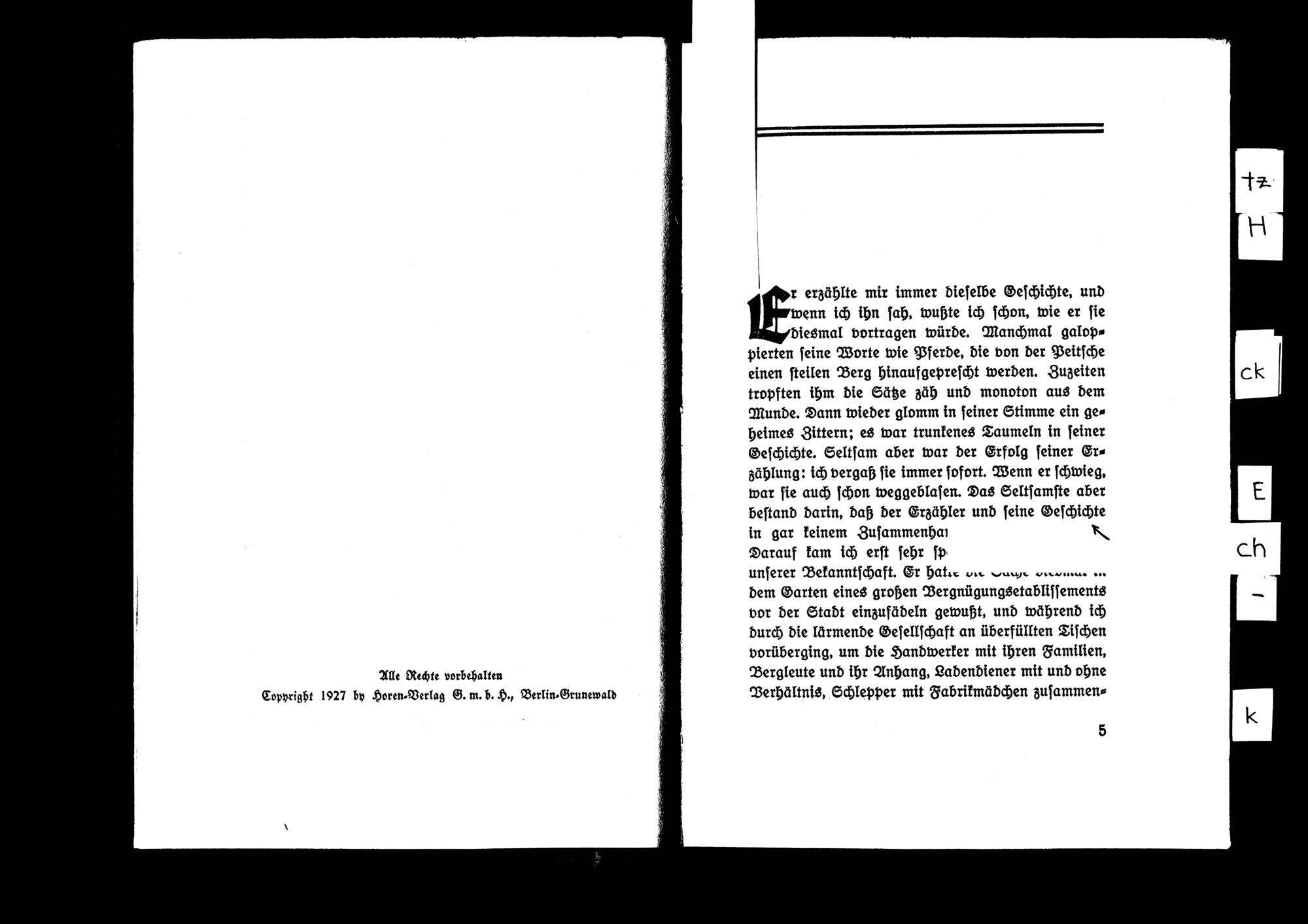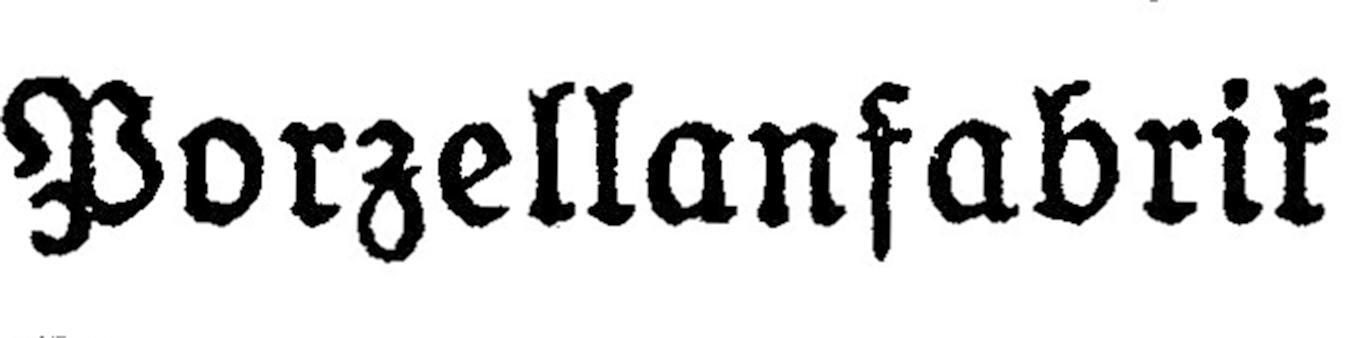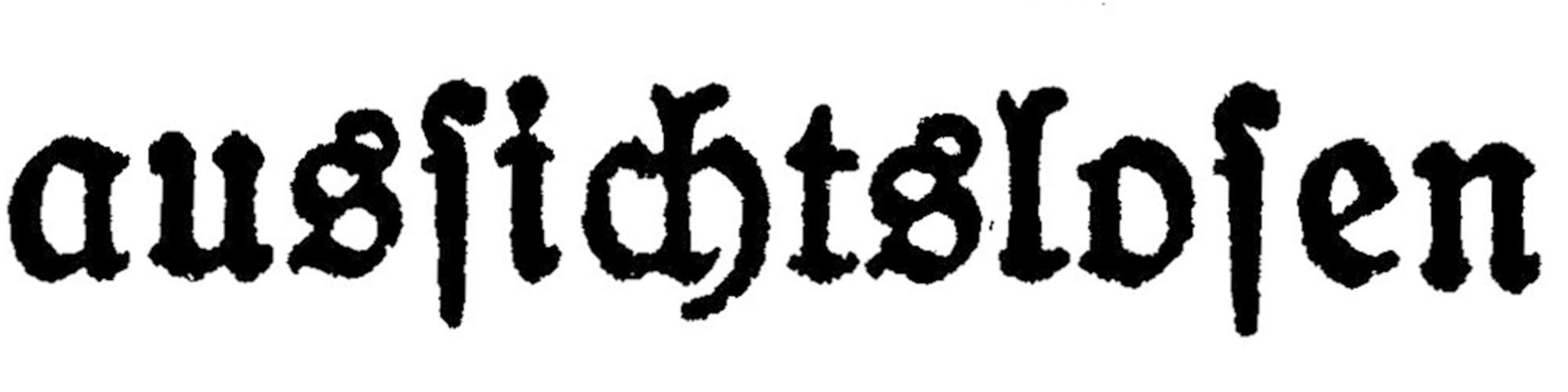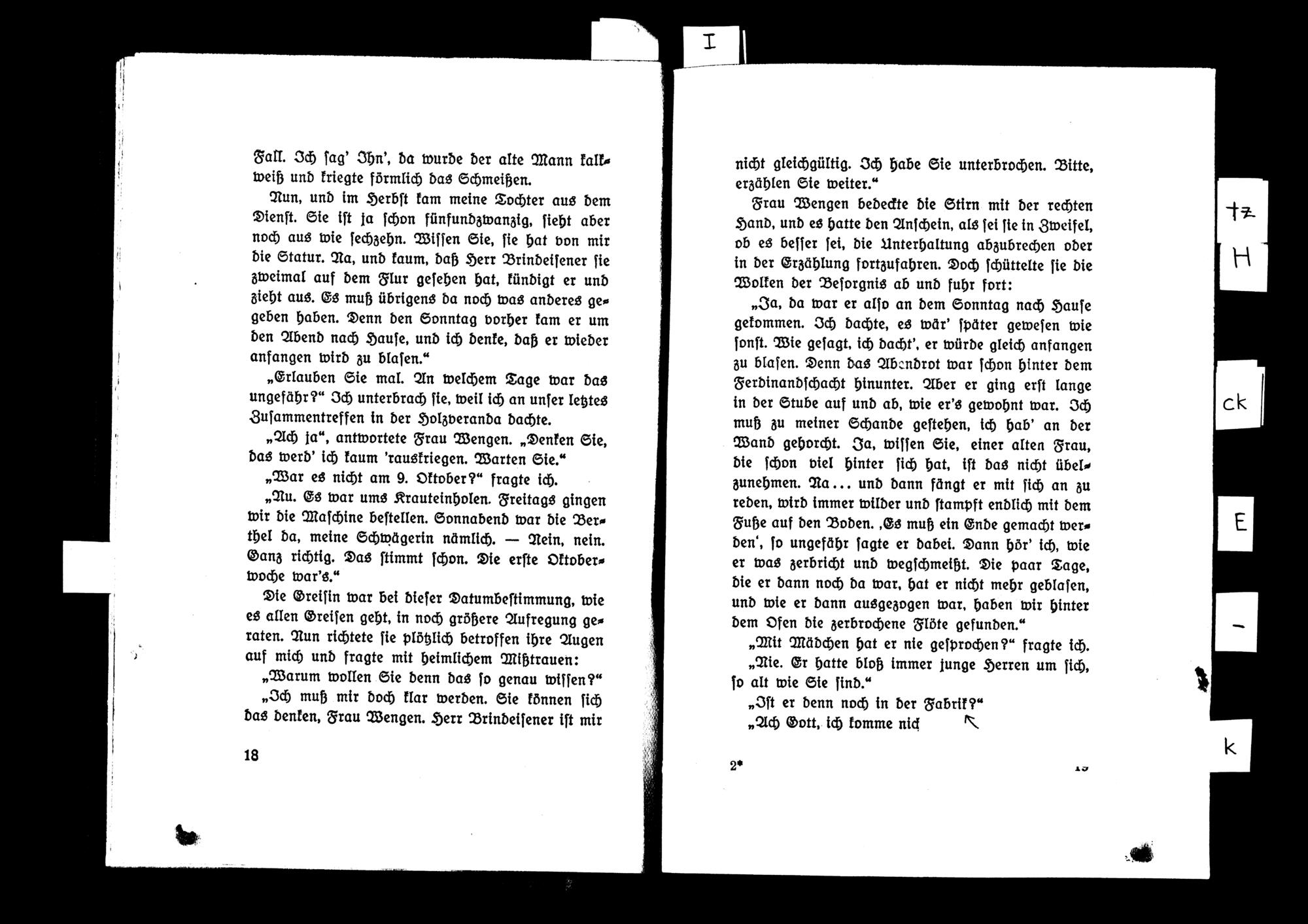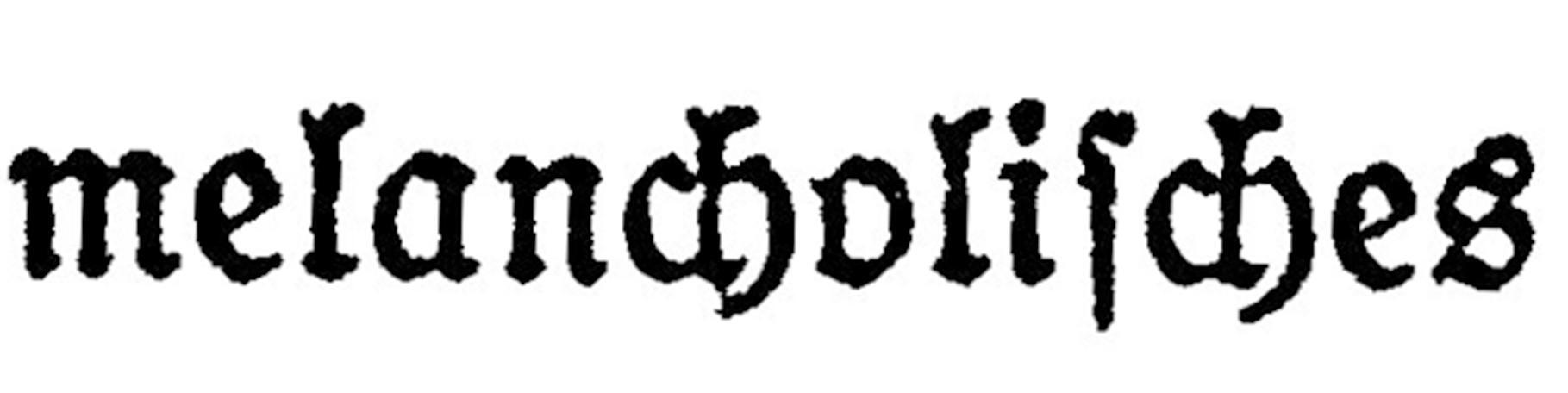
Suche Frakturschrift aus dem Buch "Peter Brindeisener" (1927 geruckt)
zuerst: ich suche nur den Schriftnamen zu Recherchezwecken. Ich habe mich bereits ein wenig mit Frakturschriften auseinader gesetzt, diese bestimmte Schrift aber noch nicht finden können. Vielleicht kann mir ja jemand weiter helfen. Das ganze brauche ich für ein Projekt, da ich in meinem Studium gerne mit der Schrift arbeiten würde.
Das Buch heißt Peter Brindeisener und ist von Hermann Steher. Meine Ausgabe ist von 1927 und vom Horen-Verlag G.m.b.H, Berlin-Grundewald produziert worden. Die Scans habe ich in schwarz-weiß einmal angehangen.